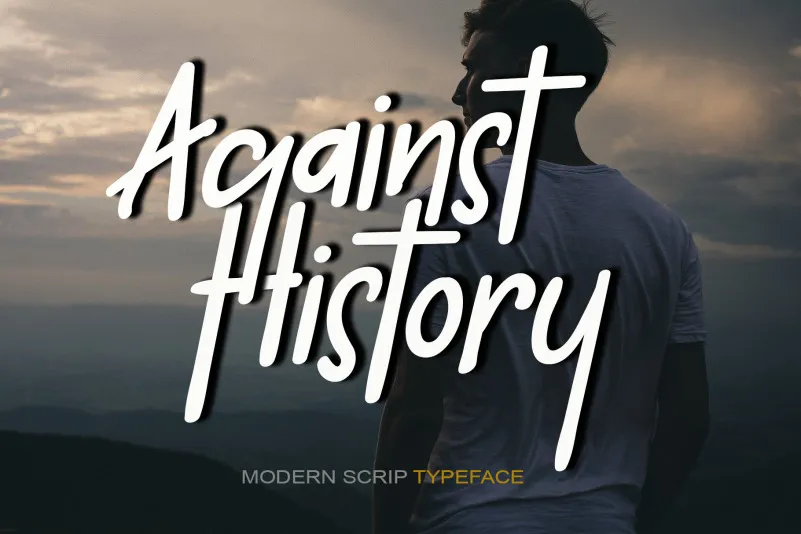
Against History Font – Fonte Grátis
Against History Font
Esta é uma fonte escrita a mão com uma aparência encantadora e versátil, adequada para uso em diversos projetos. Ela tem um toque quente e peculiar que torna cada ideia original sua própria obra de arte. Kateengciu, o designer desta fonte, nos oferece esta fonte escrita a mão como uma delícia, perfeita para explorar infinitas variações. Seja criativo, seja divertido com essa bela fonte e experimente suas possibilidades únicas e flexíveis. Ideal para um design de arquitetura minimalista ou uma composição gráfica que exibe personalidade. Não deixe esse gosto na mão escapar!